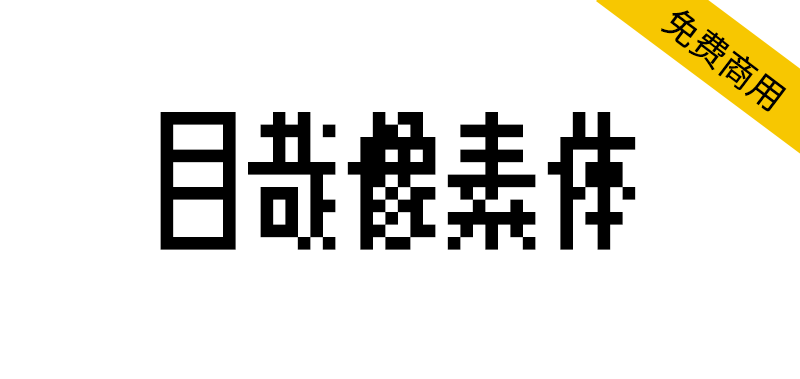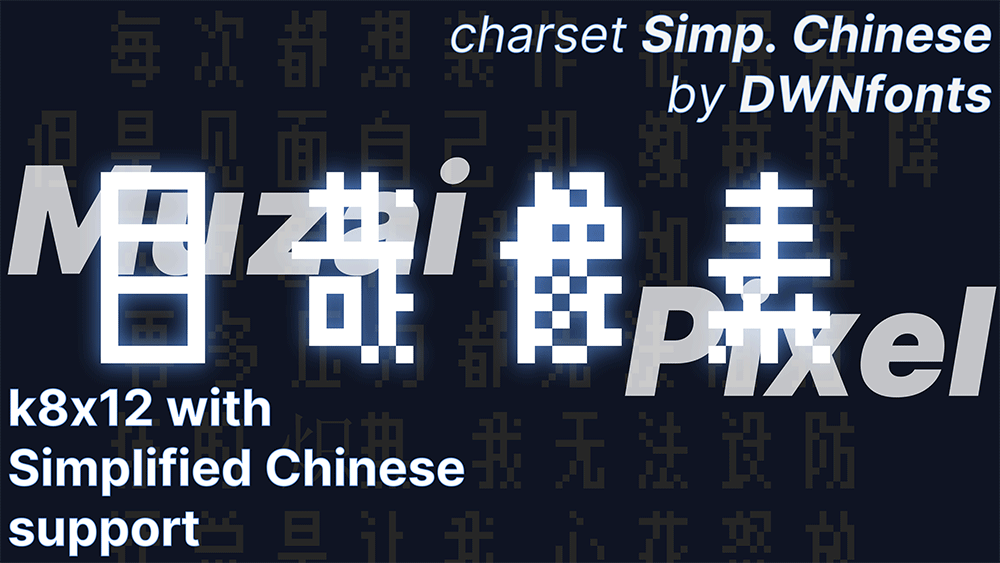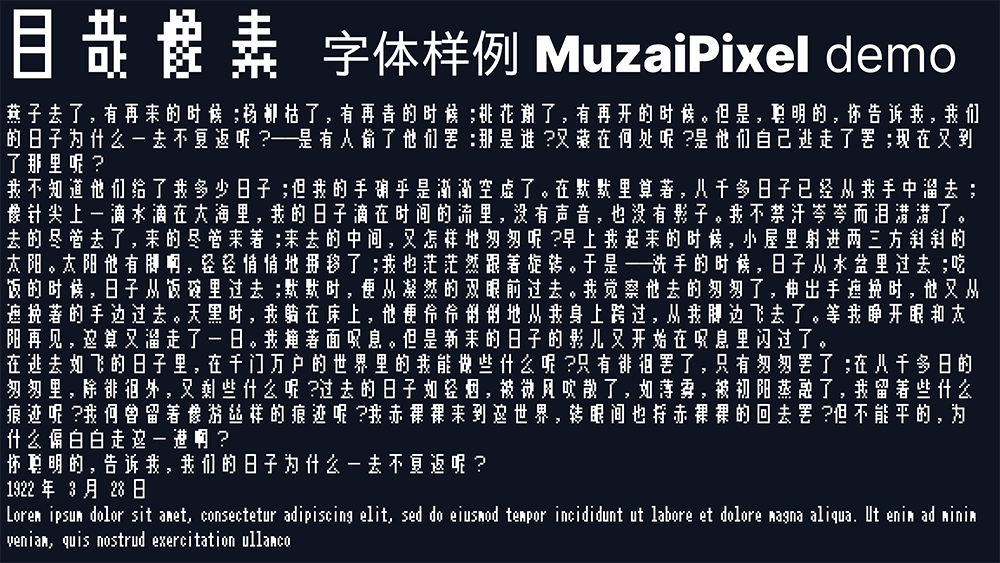
目哉像素(曾用名 k8x12j)是一个基于 k8x12 的 8x12 中日文点阵(像素)字体,这个字体的汉字覆盖率可能不尽人意,会出现缺字。
为什么有俩字体?
original 版本像素是方的,如果你的工具没有 bug 的话建议用这个
flat 版本拉宽到原来的 1.5 倍,如果你的工具有 bug,那就用这个,然后压缩一下。